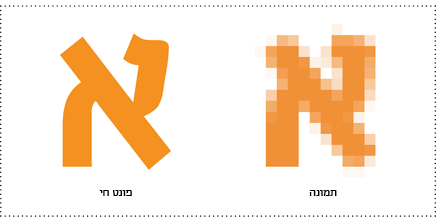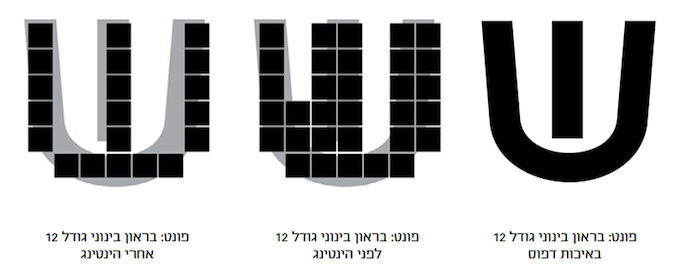
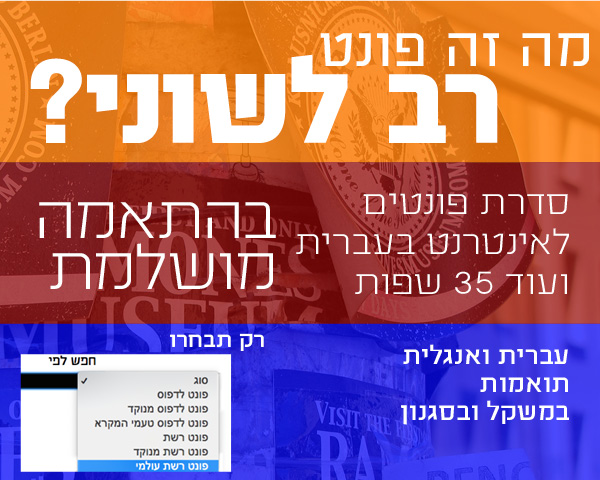
סידרת הפונטים עולמי - הסידרה החדשה למעצבי אתרים.
אין יותר התלבטות איך להטמיע באתר מספר פונטים בשתי שפות ששוקלים יותר מידי. בפונט אחד כלולות עברית ואנגלית בהתאמה מושלמת. סידרת עולמי מכילה עברית ולטינית ב-35 שפות באותו משקל, סגנון ועיצוב. בנוסף, חידוש מרענן - ספרוֹת נפרדות לעברית ואנגלית. בעברית גובה הספרוֹת לפי גובה האות ם, ובלטינית גובה הספרוֹת לפי גובה ה Caps.
מה זה בכלל פונט רשת?
כבר לא צריך להתפשר - הפונטים שהשתמשת בהם בפרינט, מעכשיו חיים גם באתר האינטרנט שלך. הנוכחות של המותג שלך ברשת תהיה עקבית על פי הקו העיצובי שלך.
בעבר, יכלו מעצבי אתרים לצפות מראש איך יראה האתר שלהם לגולשים רק בתנאי שהגבילו עצמם והשתמשו בפונטים הבסיסיים של מערכות ההפעלה, שממילא יש לכולם. רשימת פונטים דלה זו כונתה "גופני רשת בטוחים", ואם רצית כותרות בפונט מיוחד, היה עליך לשתול קבצי תמונה עם כל הכותרות ועם כל המגבלות שבכך.
תמונה של פונט לעומת פונט חי
ואז המציאו את טכנולוגיית Font-face – הפונטים יושבים על שרת האתר, והדפדפן יודע "לשדר" אותם כפונטים חיים יחד עם דף האינטרנט למחשב של הגולש. כשמשתמשים בתקן של Font-face, הדפדפן מוריד את הפונט באופן זמני ומשתמש בו לתצוגה חיה של הטקסט. למותר לציין שהפונטים עוברים אופטימיזציה להבטחת איכות תצוגה מירבית. סוף סוף, חופש עיצובי למעצב וללקוח.
יתרונות מידיים:
1. עקביות עיצובית, הפרינט עובר לאינטרנט בלי פשרות של פונטים.
2. הפונטים נשארים קריאים וצלולים גם בהגדלה או בהקטנה של - נגישות לבעלי מוגבלויות.
3. מכיוון שמדובר בטקסט, העמודים נטענים במהירות.
4. הטקסט זמין למנועי החיפוש, ומאפשר קידום טוב יותר של האתר במנועי החיפוש.
5. ניתן להעתיק טקסט חי ואף לכתוב באמצעותו (במילוי טפסים מקוונים למשל).
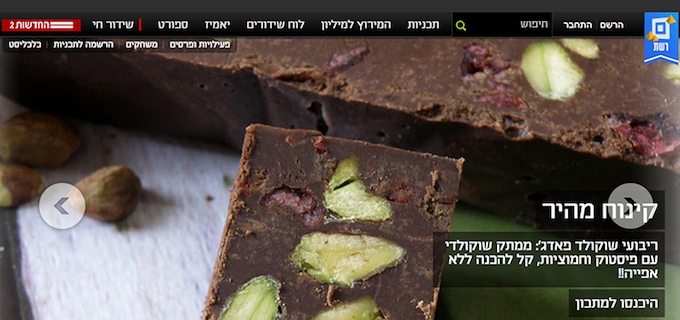
פונט חי "אפליקציה" באתר רשת
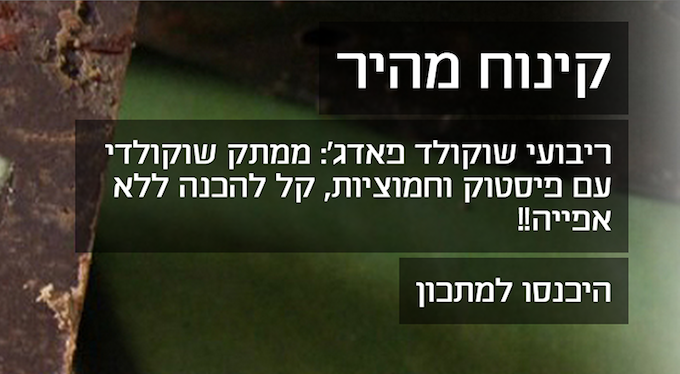
ובהגדלה, הפונטים חדים וצלולים.
פונטים חיים ברשת - איך זה עובד?
הפונט לא באמת מותקן על המחשב של הגולש. הדפדפן, באופן זמני, משתמש בו רק לתצוגה חיה של הטקסט.
מה מייחד את גופני הרשת של מסטרפונט?
כעת ניתן לרכוש ולהטמיע כל פונט מספריית מסטרפונט (כולל כל משפחת נרקיס) באתר ללא התחייבות וללא דמי מנוי. פונטי הרשת שלנו עוברים טיפול ידני מיוחד (Hinting) המבטיח את חדותם על המסך בכל רזולוציה. מאחר שאין לנו שליטה איפה תכתבו בפונט על גבי המסך, הרי שעלול לקרות מצב בו האות שנכתבת עלולה ליפול מחוץ לשורת הפיקסלים של המסך וצורתה תיפגע. עבור כל אות ואות בפונט, אנחנו כותבים תוכנית ובה נקבע איזה פיקסלים להדליק ואיזה לכבות, בכל גודל נתון. כמובן שבגודל 12 יודלקו פיקסלים אחרים מאשר בגודל 13 ולפיכך, אנחנו מצמידים לכל אות שבפונט מעין "תוכנית עבודה" ובה הוראות איזה פיקסל רצוי להדליק בכל גודל שתבחרו בכדי לקבל תוצאה חדה על המסך. בבסיס התכנות הזה מצויה החוקיות הויזואלית איתה אנחנו מנסים לשמר את היחוד הצורני של האות על מפה של פיקסלים.